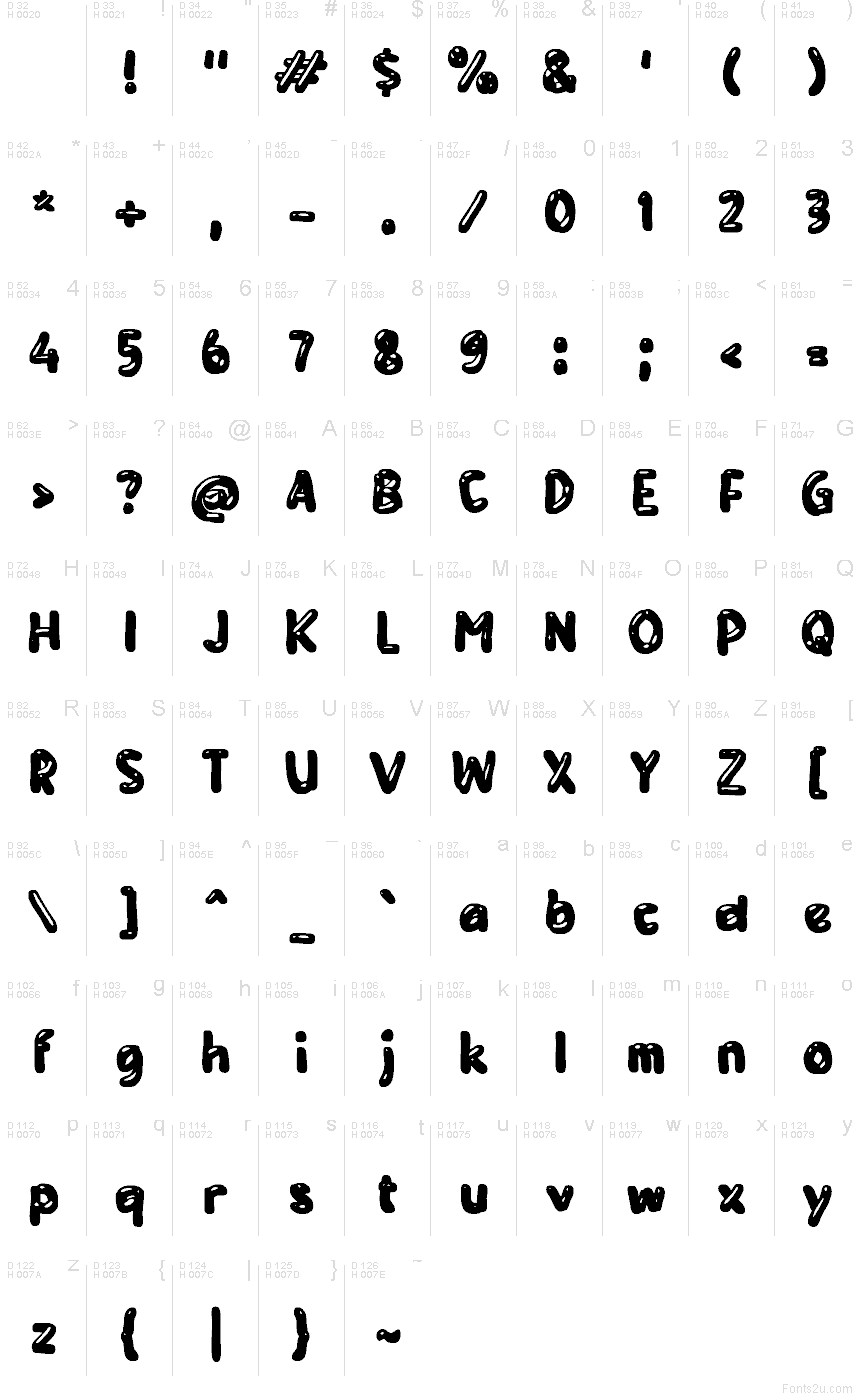
Zabekat
Zabekat - бесплатный мультяшный дисплейный шрифт от Wep, который превращает буквы в мягкие черные пятна с вырезами-бликами, придающими им объемный и глянцевый вид. Этот округлый, «плавный» ритм придает дизайну легкий озорной характер, больше напоминая нарисованные от руки наклейки, чем обычный комиксный шрифт.
Он отлично смотрится на обложках детских книг, упаковках снеков, приглашениях, миниатюрах для YouTube и в оформлении вывесок, где такая «пухлая» форма говорит сама за себя. Шрифт идеален для коротких заголовков и логотипов: надутые формы и яркие блики создают мощный графический акцент без необходимости в дополнительном декоре.